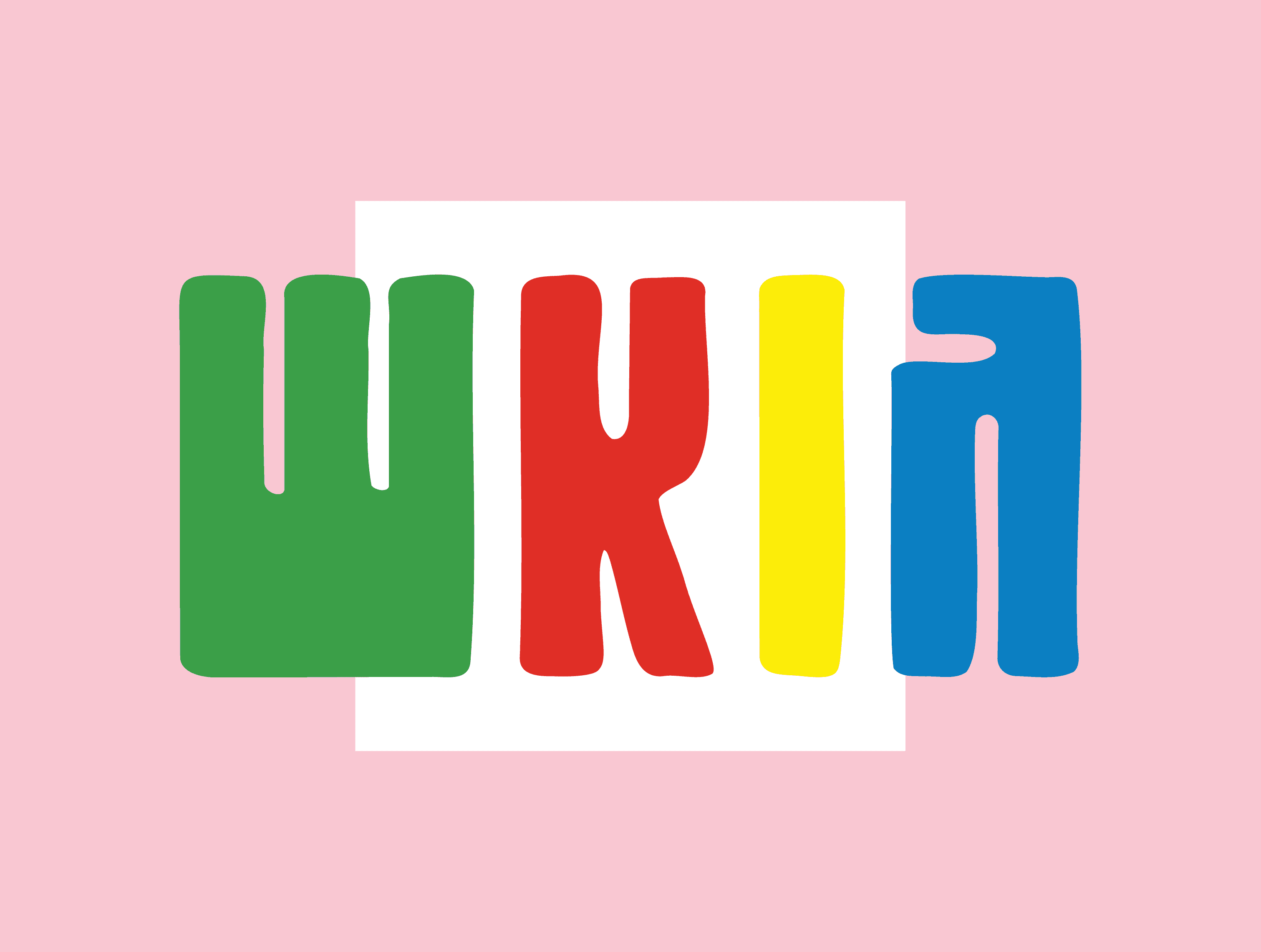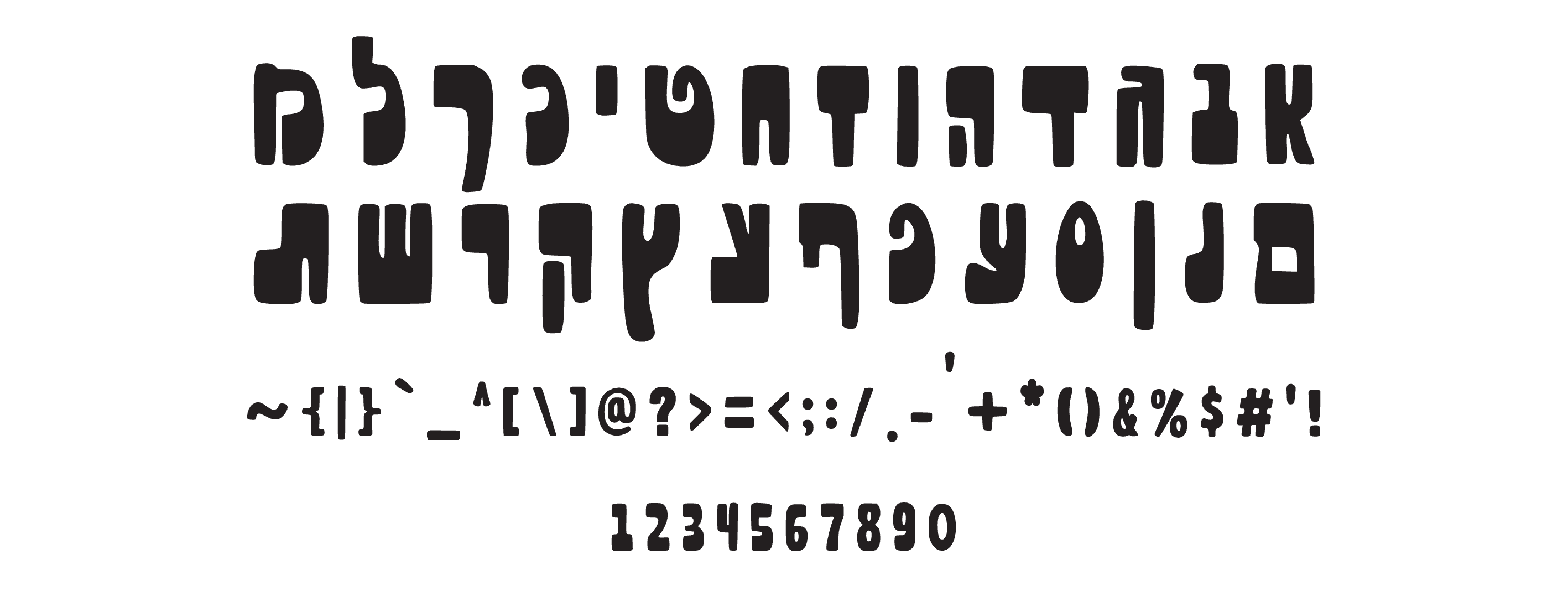
פונט גואש
פונט עברי צבעוני וידני, מושלם לעיצובים לילדים, פוסטרים ומוצרי יצירה.
גואש — הפונט שמצייר חיוך על כל עיצוב
יש פונטים שבאים לעצב, ויש כאלה שפשוט באים לשחק!
גואש הוא פונט צבעוני, ידני, מלא שמחה ואנרגיה, שמרגיש כאילו נמרח על הדף במכחול.
הוא מביא איתו אווירה שובבה ועליזה, עם קווים עבים, מעוגלים ומעט גסים — ממש כמו עבודת יד אותנטית.
הפונט הזה מושלם לכל עיצוב שרוצה להרגיש קצת ילדותי, שמח ומלא חיים — כזה שמקפיץ צבע לכל פרויקט.
איפה הוא מרגיש בבית?
🎨 פוסטרים לילדים
🎨 מוצרי יצירה, חוברות ודפי פעילות
🎨 כותרות צבעוניות ומזמינות
🎨 עיצובים לקיץ, פסטיבלים ואירועי קהילה
למי הוא מתאים?
למעצבים יצירתיים, למותגים צבעוניים, ולכל מי שרוצה להוסיף טאץ' ילדותי ושמח לעיצוב.